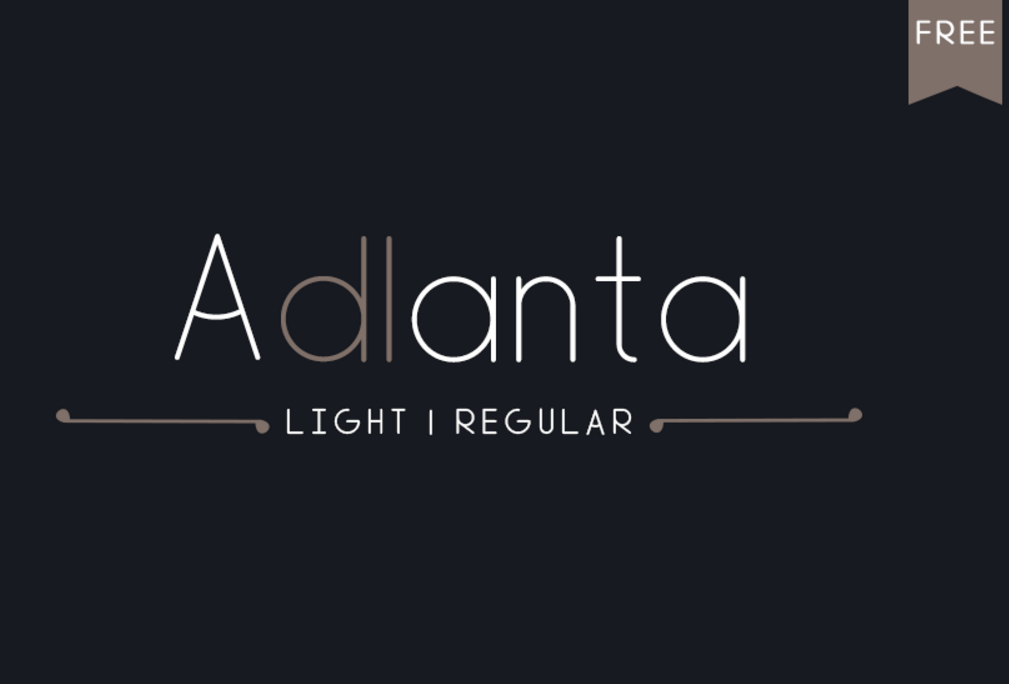
A Adlanta Font é uma elegante tipografia sans-serif que traz uma mistura harmoniosa de modernidade e sofisticação. Suas linhas retas e diretas se destacam perfeitamente em qualquer projeto, seja ele para websites, editoriais ou design gráfico digital. Seu design minimalista e clean combina perfeitamente com qualquer elemento visual, garantindo que sua marca seja sempre notável e forte. Criada pelo designer crash2405, a Adlanta Font é uma escolha perfeita para quem busca um estilo simples e moderno, sem comprometer a precisão dos detalhes. A fonte se torna um aliado valioso no processo criativo, permitindo que você transmita sua mensagem de maneira clara e eficaz em qualquer formato. Com Adlanta Font em seu arsenal, o design digital ganha uma nova expressividade e qualidade.